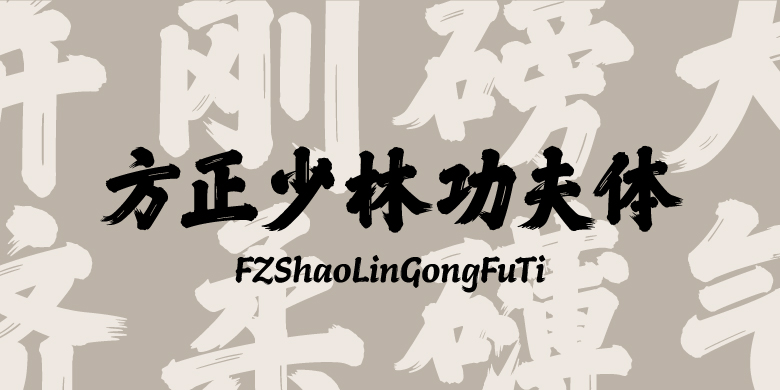
フォントサービス「方正 LETS」「FONTPLUS」に方正(北京北大方正電子有限公司)の日本語5書体を追加
米国 Monotype Imaging Inc.の日本法人Monotype株式会社(東京都港区、以下 Monotype)は、フォントサービス「方正 LETS」ならびにWebフォントサービス「FONTPLUS」に「方正少林功夫体(ほうせいしょうりんかんふーたい)」をはじめとする日本語5書体の提供を、2025年8月27日(水)より開始しました。
少林功夫(カンフー)のイメージを完全に表現した書体
方正少林功夫体(ほうせいしょうりんかんふーたい)
方正少林功夫体(ほうせいしょうりんかんふーたい)は、中国嵩山少林寺の「千崖万壑(せんがんばんがく)」碑をベースに開発した書体です。フォントデザインは、筆画の主幹部分を滑らかな曲線で設計し、すっきりとした味わいを表現しました。筆画の始めと終わりには、毛筆書法の質感を再現し、飛白牽糸のデザイン要素を融合させ、石刻の持つ堅牢な素朴さと同時に毛筆字の細部と感情を持つようにしています。
本書体は大気磅礴で、柔らかさと堅牢さを兼ね備え、行書の流れるような美しさと碑文の安定感を併せ持ち、少林功夫(カンフー)のイメージを完全に表現しています。
方正柳公権楷書(ほうせいりゅうこうけんかいしょ)
方正蘇軾行書(ほうせいそしょくぎょうしょ)
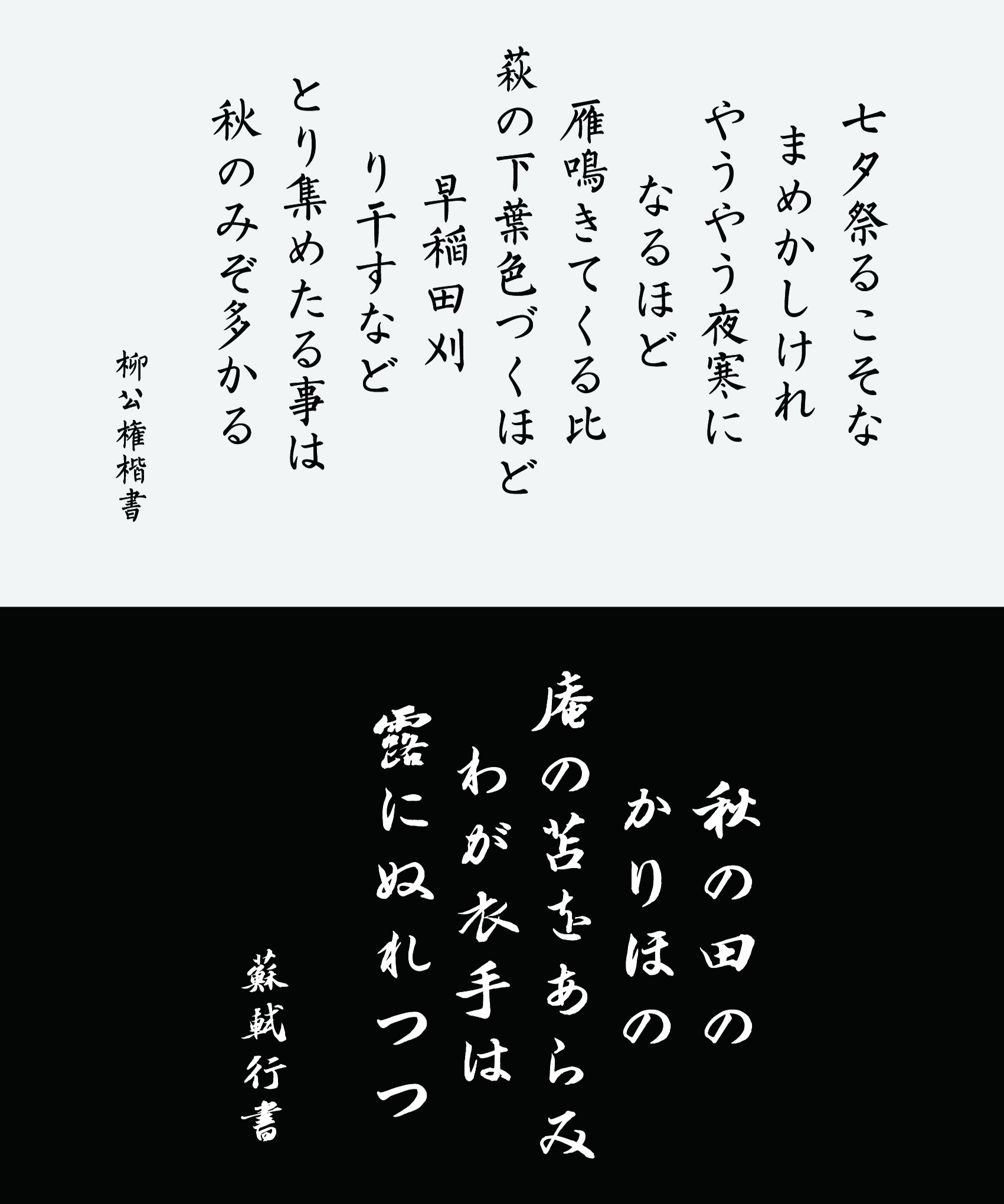
方正柳公権楷書(ほうせいりゅうこうけんかいしょ) は、中国唐代の書道家である柳公権の楷書をベースに開発されました。本書体は、筆勢は力強く、形は整然としており、厳密さの中にも疎らな美が表れています。
方正蘇軾行書(ほうせいそしょくぎょうしょ)は、中国北宋の書道家である蘇軾の法帖(信札、手巻き)、刻帖をベースに開発された書体です。本書体の筆法は豊満で、文字の構造は平たく、横は軽く縦が重くなっております。また撥ねや捺(右払い)が伸びやかで、字形の変化に応じて配置も工夫されており、自然で厚みと深みのあるデザインが特徴です。
方正爨宝子碑楷書(ほうせいさんぽうしひかいしょ)
方正顔真卿楷書(ほうせいがんしんけいかいしょ)
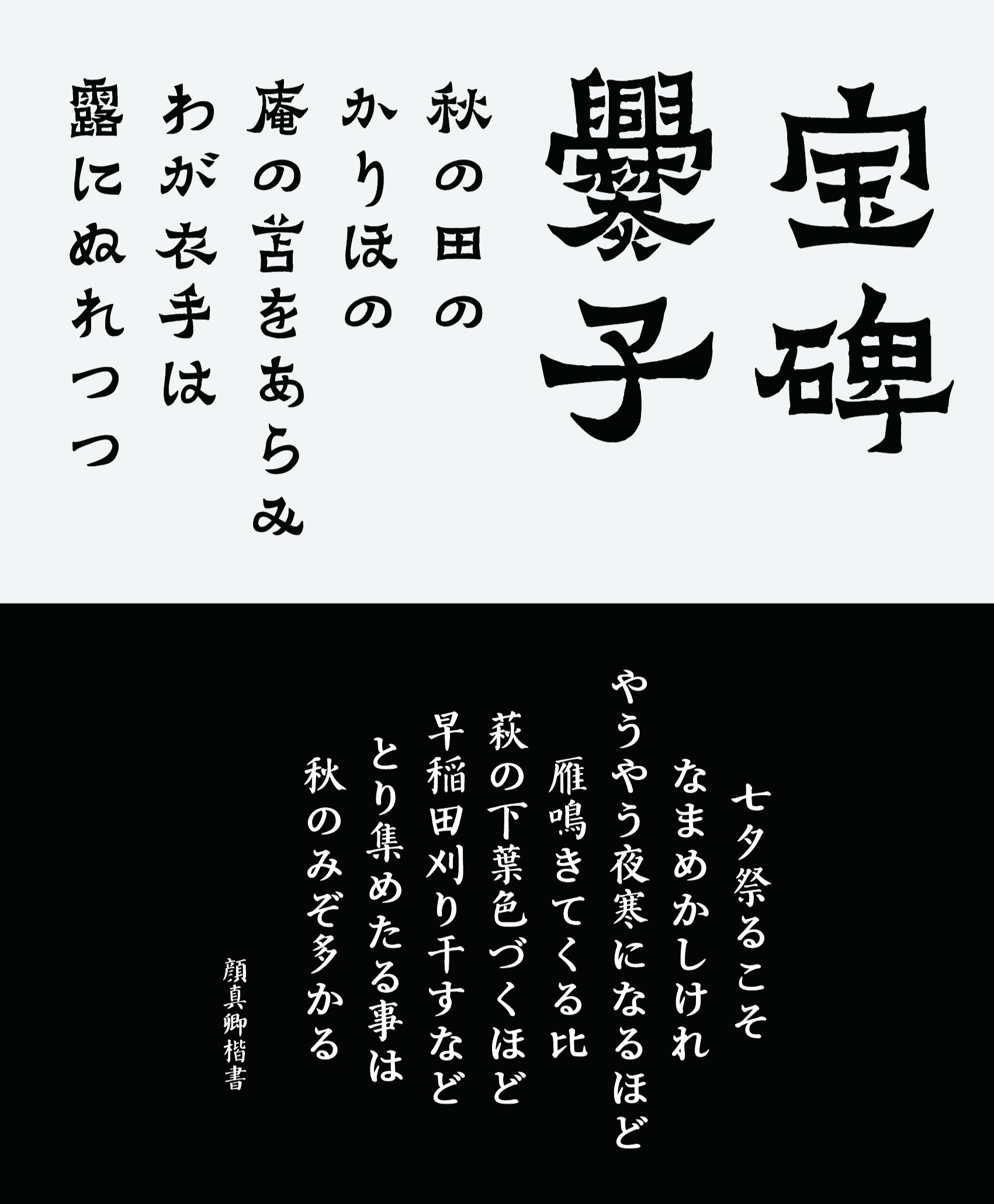
方正爨宝子碑楷書(ほうせいさんぽうしひかいしょ) は、中国東晋代に建てられた地元豪族の墓碑『爨宝子碑』をベースに開発されました。本書体は、質朴で厚みがあり、大胆でありながら繊細で、率直で力強い風格があり、特異な姿勢が自然と表現されています。また、字形の構造と情緒からも隷書から楷書に至る変遷を楽しめます。
方正顔真卿楷書(ほうせいがんしんけいかいしょ)は、中国唐代の書道家である顔真卿の『顔勤礼碑』をベースに開発されました。このフォント構造は広く大胆で、勢いがあります。力強さがありながらも品格も所持しており、厳格で朴素で、壮大な雰囲気を示しています。